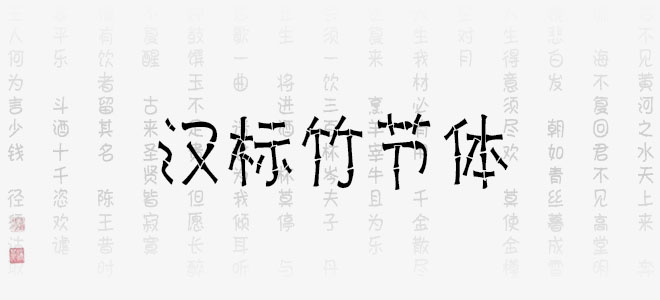
漢標竹節(jié)體字體是漢標字庫中一款非常個性的藝術(shù)字體,通常字形中的點、撇、捺、鉤、提等筆畫各具面目,筆畫運用了竹節(jié)圖形元素來構(gòu)建,把這些筆畫做成了竹節(jié),概括為飄逸的竹節(jié),并且使左右舒展的筆畫盡量對稱,最大限度地簡化筆畫竹節(jié)造型。歡迎喜歡漢標竹節(jié)體的朋友前來下載使用。
漢標竹節(jié)體